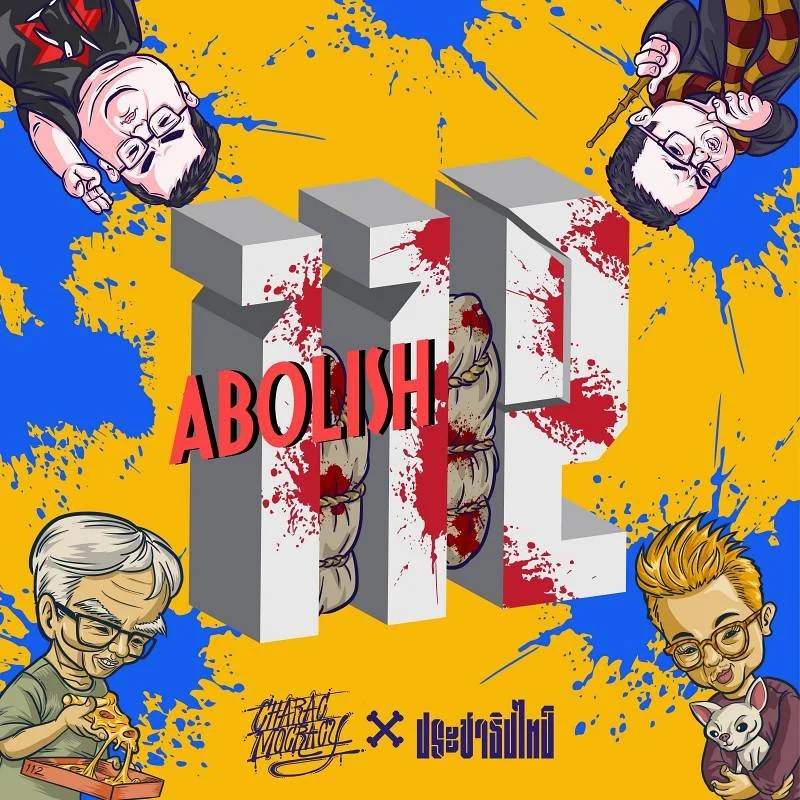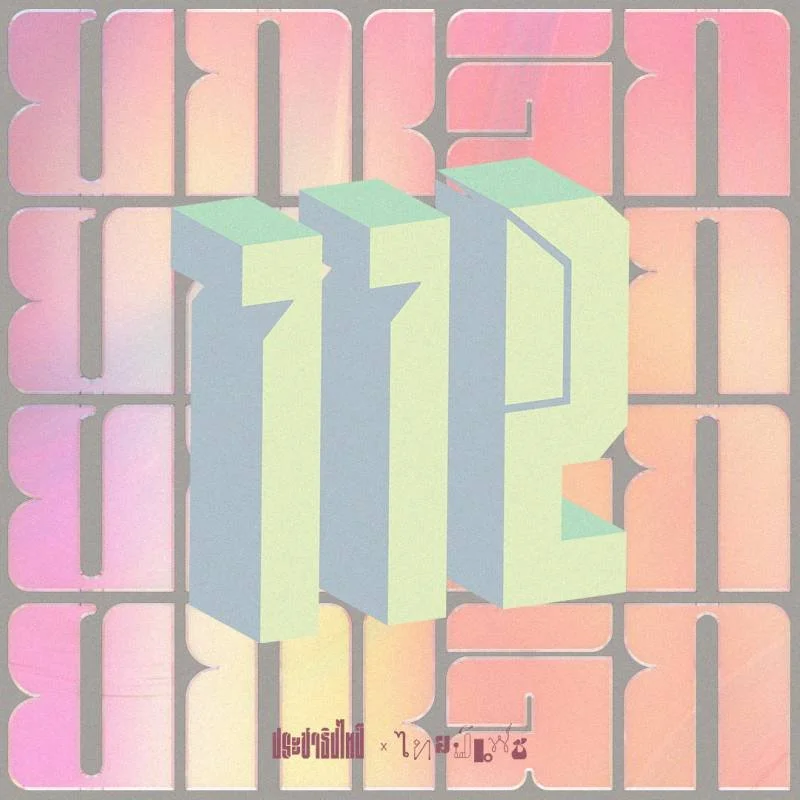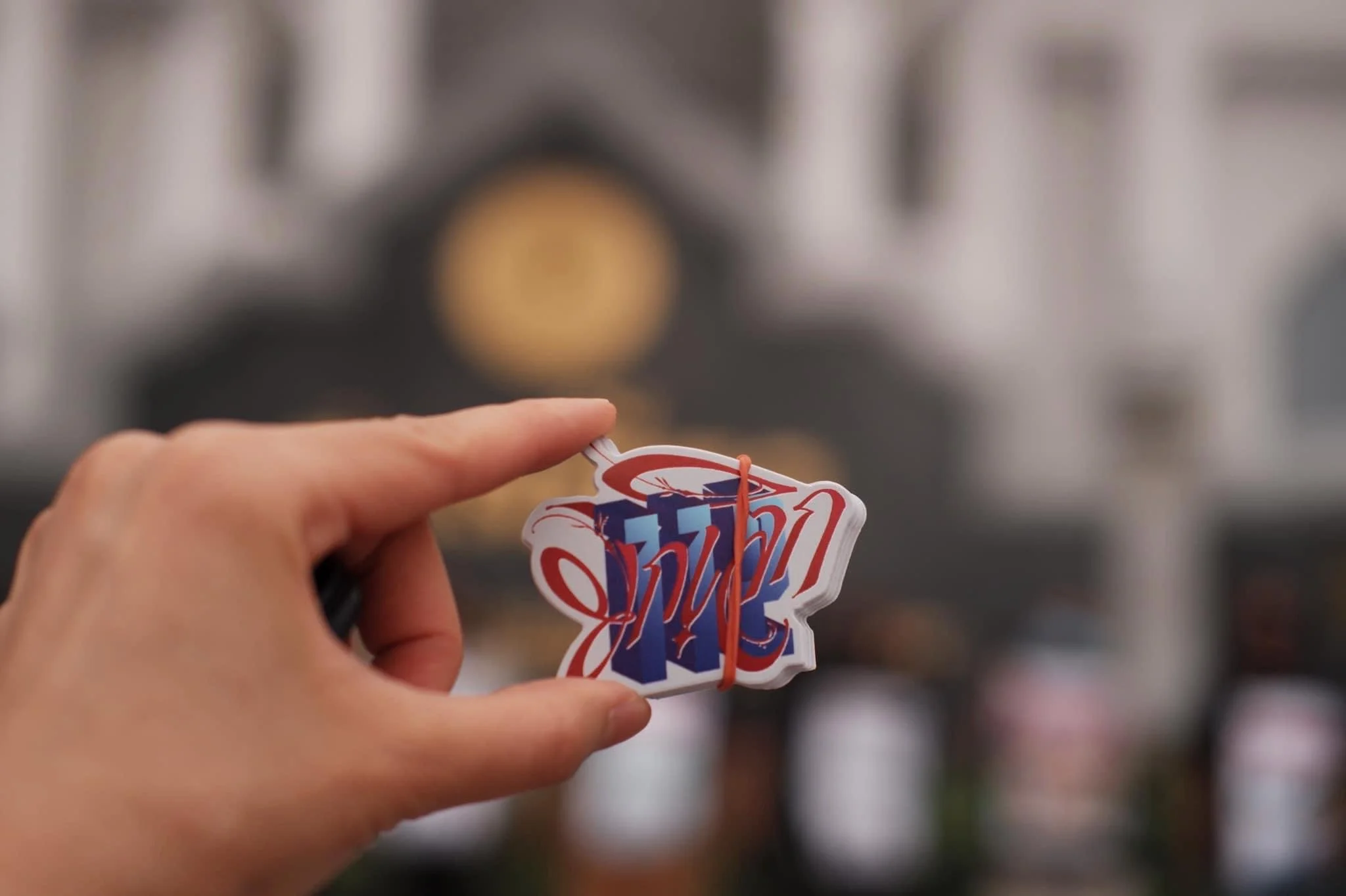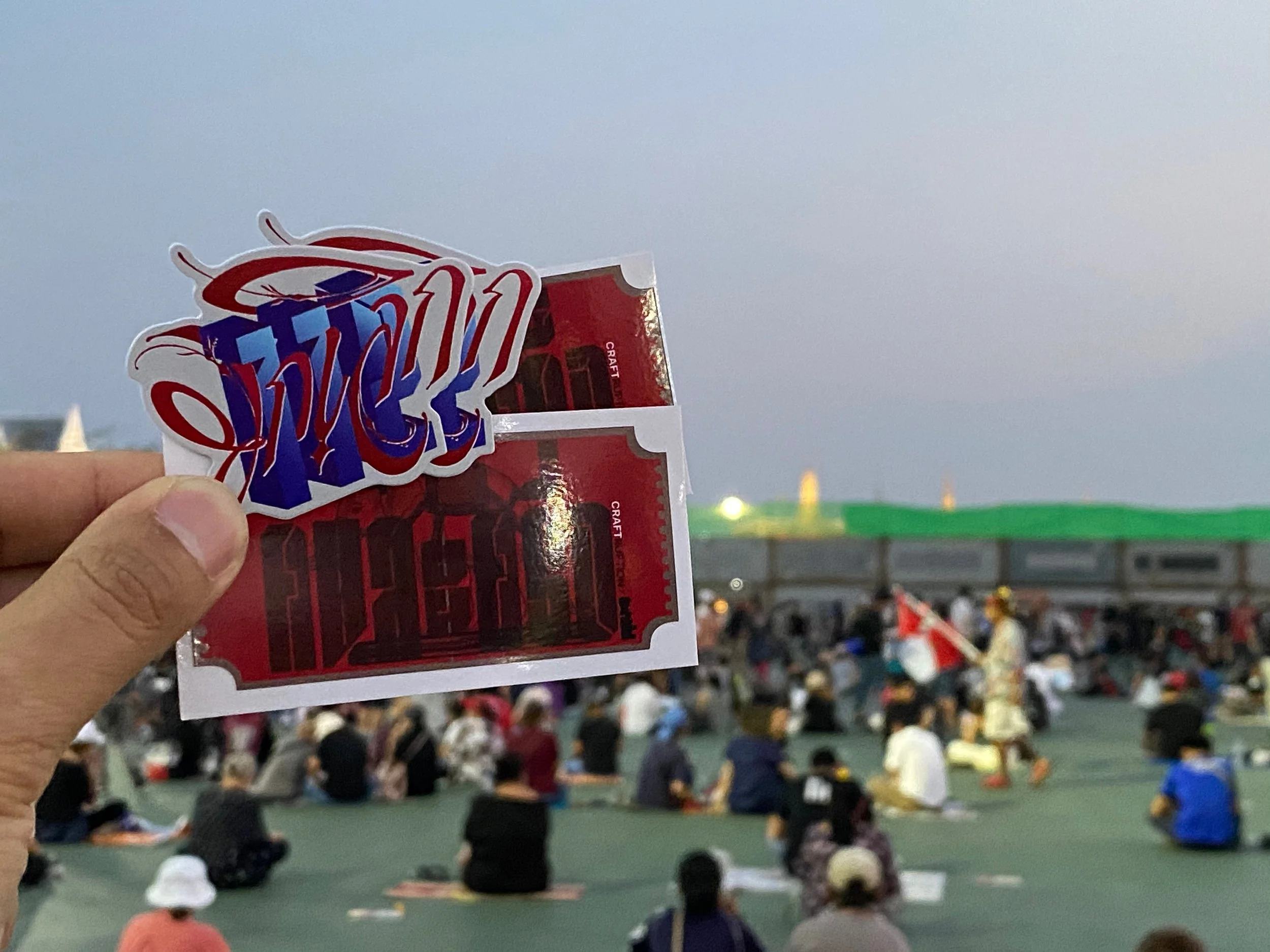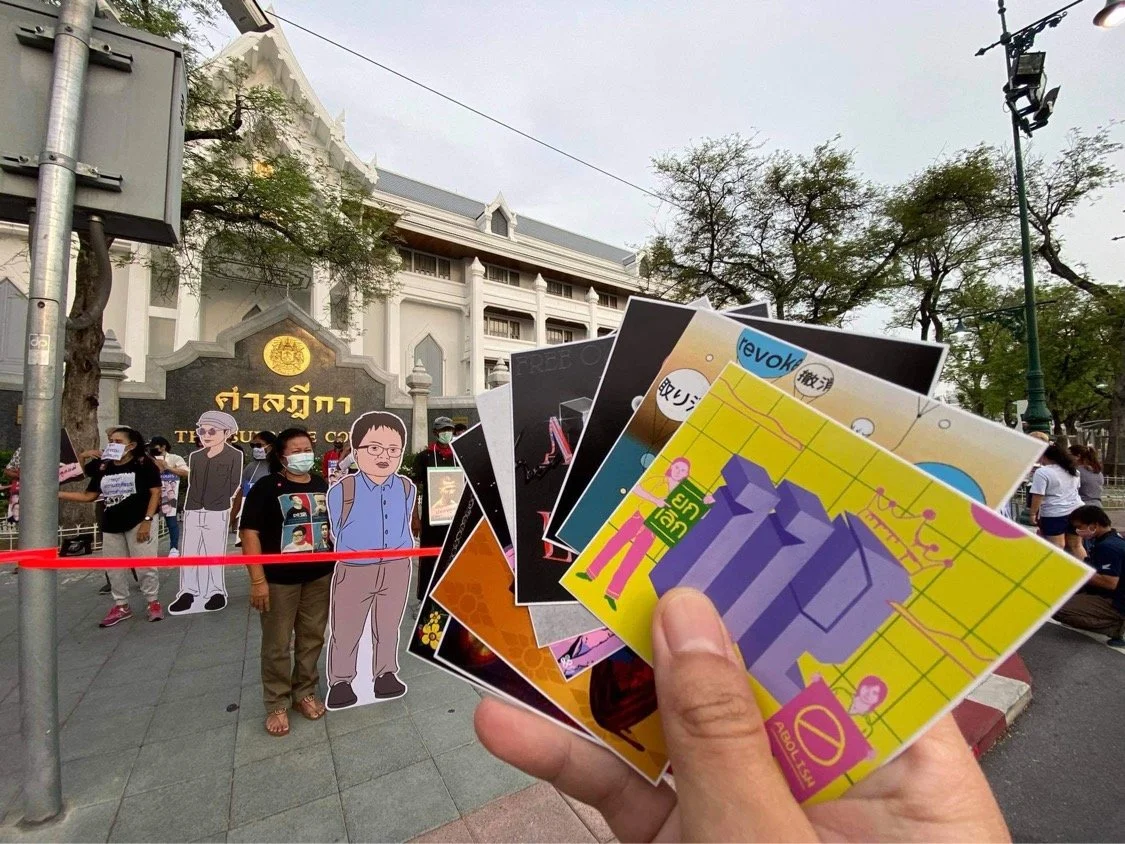
เราอยากให้ยกเลิก 112
ในช่วงต้นปี 2564 เราได้ร่วมงานกับ Sorravis P. ยอดฝีมือ calligraphy ออกสติกเกอร์ “ยกเลิก 112” ภาพนี้ขึ้นมา เป็นการผสานกันระหว่างตัวเลข 112 แบบ 3 มิติในฟอนต์ทางม้าลาย กับข้อความ “ยกเลิก” โดยคุณ Sorravis
เมื่อมองเห็นความเป็นไปได้ของการร่วมมือกับนักสร้างสรรค์ท่านอื่น เราจึงเริ่มแคมเปญ #เราอยากให้ยกเลิก112 ขึ้นบน Facebook และ Instagram โดยเปิดให้โหลดเทมเพลทที่มีตัวเลข “112” แล้วเขียนข้อความ “ยกเลิก” ในแบบของตัวเอง ส่งกลับมาเพื่อชิงรางวัลสติกเกอร์แบบแรกนี้ และของที่ระลึกอื่นๆ
เราคาดหวังไว้ว่าจะรวบรวมผลงานให้ได้ครบ 112 ชิ้นเพื่อนำไปจัดแสดง แต่ท้ายที่สุดมีผู้ส่งผลงานมาร่วมกิจกรรมประมาณ 50 ชิ้น
หลังจากที่เราได้นำสติกเกอร์ที่ร่วมออกแบบกับ Sorravis P. ไปแจกตามม็อบและกิจกรรมต่างๆ มาหลายครั้ง จนมีผู้สนใจต้องการซื้อสติกเกอร์เข้ามาตลอด แต่เราไม่อยากขาย และต้องการให้เงินของผู้สนับสนุนไปช่วยการเคลื่อนไหวในภาพใหญ่ เราจึงคัดเลือกผลงาน 12 แบบจากเพื่อนๆ มาผลิตเป็นสติกเกอร์ ขนาด 7.5 x 7.5 ซม. แล้วเปิดให้นำสลิปการโอนเงินเข้าบัญชีของกองทุนราษฎรประสงค์, กองทุนดาตอร์ปิโด และศูนย์ทนายความเพื่อมนุษยชน มาแลกสติกเกอร์ วิธีนี้ทำให้เราได้ยอดเงินบริจาคประมาณ 3 เท่าของค่าผลิตสติกเกอร์
หลังจากนั้นสติกเกอร์เหล่านี้ก็ถูกนำไปแจกจ่ายในหลายช่องทาง เช่น ส่งให้ผู้ลี้ภัยในต่างประเทศ แจกในม็อบให้เอาไปแปะบนแนวคอนเทนเนอร์ และนำไปแจกในกิจกรรมยืนหยุดขังอีกหลายครั้ง